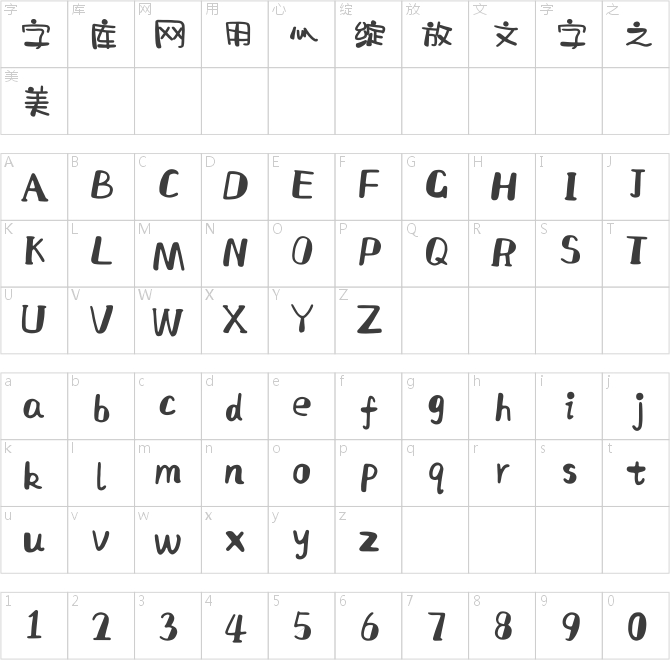
字體名稱: 字心坊pop團
字心坊pop團圓體
POP為point of purchase。即“購買點廣告”,又可譯成“店前廣告”。最早主要應用于超市賣場及各類零售終端專賣店等,既能使整體版面更活潑,又可起到有效的視覺表達,刺激引導消費。此款字體是偏圓潤、可愛的風格,保留了pop字體的特性,同時兼具了識別性。用于平面海報、網頁、影視、包裝等都有極佳的視覺效果。